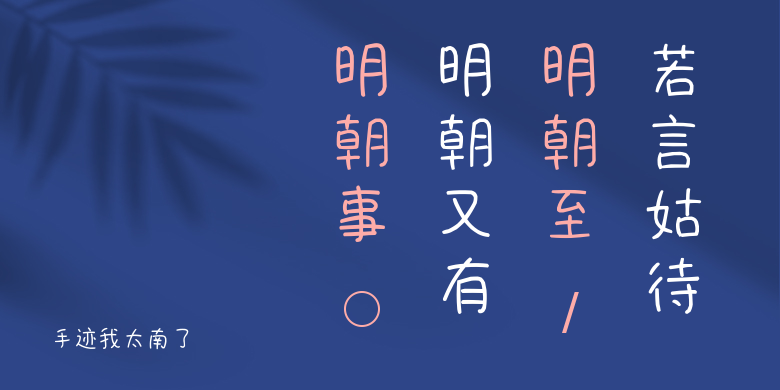
手迹我太南了
手迹我太南了,这款字体结构工整、笔画清晰,兼顾美观与易读性,适用于标题、正文、海报、包装、LOGO 等多种场景。字形优雅稳定,风格百搭耐看,适配日常排版与创意设计,让文字呈现更舒适、更具质感。手迹我太南了一笔一画,皆是细节,以均衡的比例、流畅的线条打造舒适视觉体验,字形端正大气,风格简约现代。无论是商业设计、品牌宣传还是日常排版,都能轻松驾驭,让文字更有格调与力量。手迹我太南了字体下载。